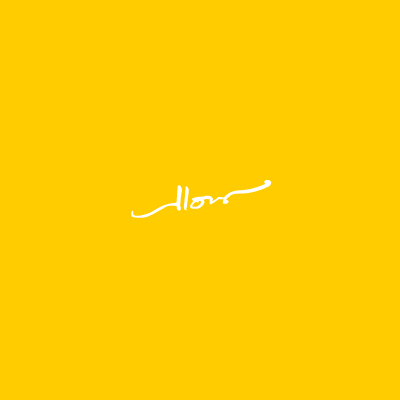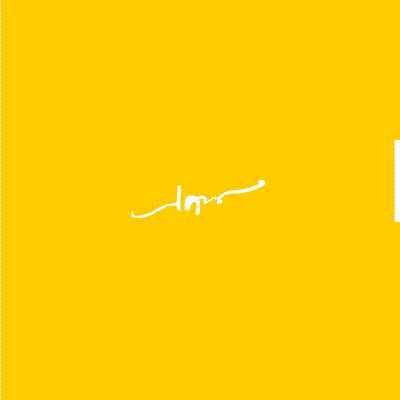
โชว์ลายเซ็น:
ใช้มาหลายปีละ
สวยดีแฮะ ชอบ+1
:30: โคตรลงทุนเลยว่ะเคน
นั่นมันลายเซ็นไอ้โต้ง :07:
แหว่งไปนิดนึงว่ะเคน :08:
มันเป็นเอกลักษณ์อยู่แล้วครับ พอพี่แอนมาเลียนแบบก็เลยทำให้ตรงจะได้ไม่เหมือนมาก
ฟ้องกรมทรัพย์สินทางปัญญาเลยเค๊น :07:
ชอบเขียนหนังสือในคอมเอียงขึ้น :33: